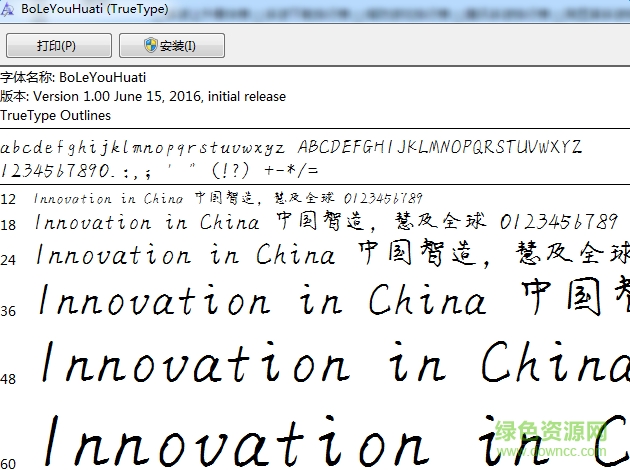
藝術(shù)油畫(huà)體
藝術(shù)油畫(huà)體字體是一款超好用的中文個(gè)性字體,字體非常具有藝術(shù)氣息,對(duì)于喜愛(ài)藝術(shù)的朋友來(lái)說(shuō)這款字體絕對(duì)是你必不可少的收藏之一,喜歡的用戶(hù)就趕快來(lái)綠色資源網(wǎng)免費(fèi)下載收藏吧!
藝術(shù)油畫(huà)體字體是一款極具個(gè)性的字體,該字體十分飄逸,彰顯了自己的個(gè)性,有喜歡的朋友可以來(lái)綠色資源網(wǎng)下載使用!